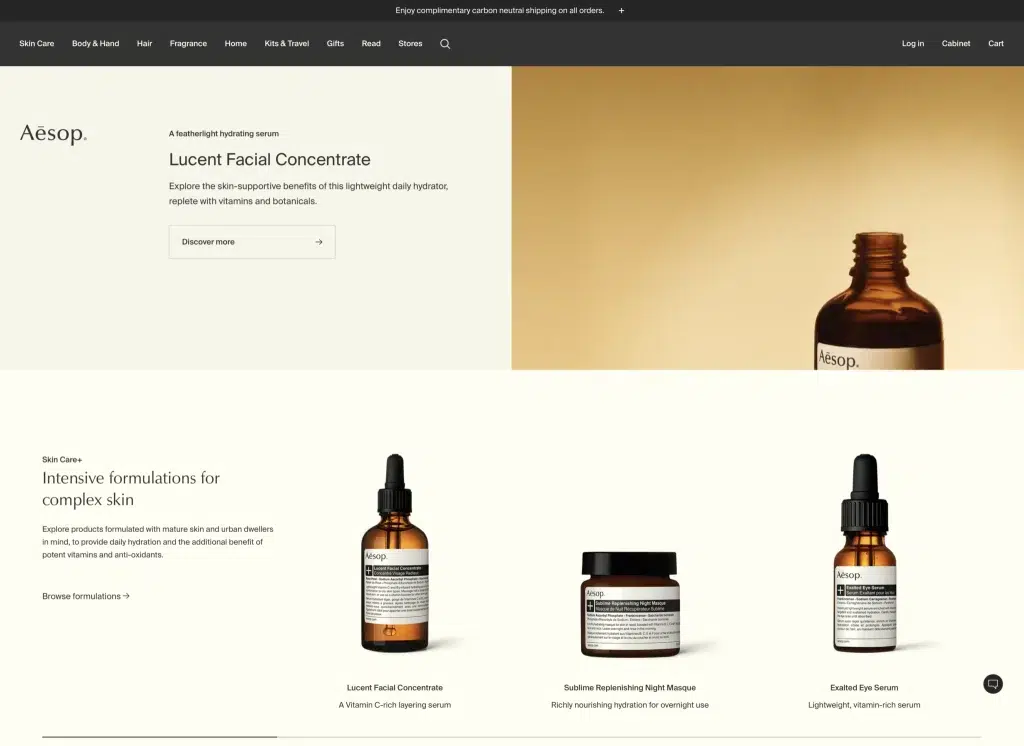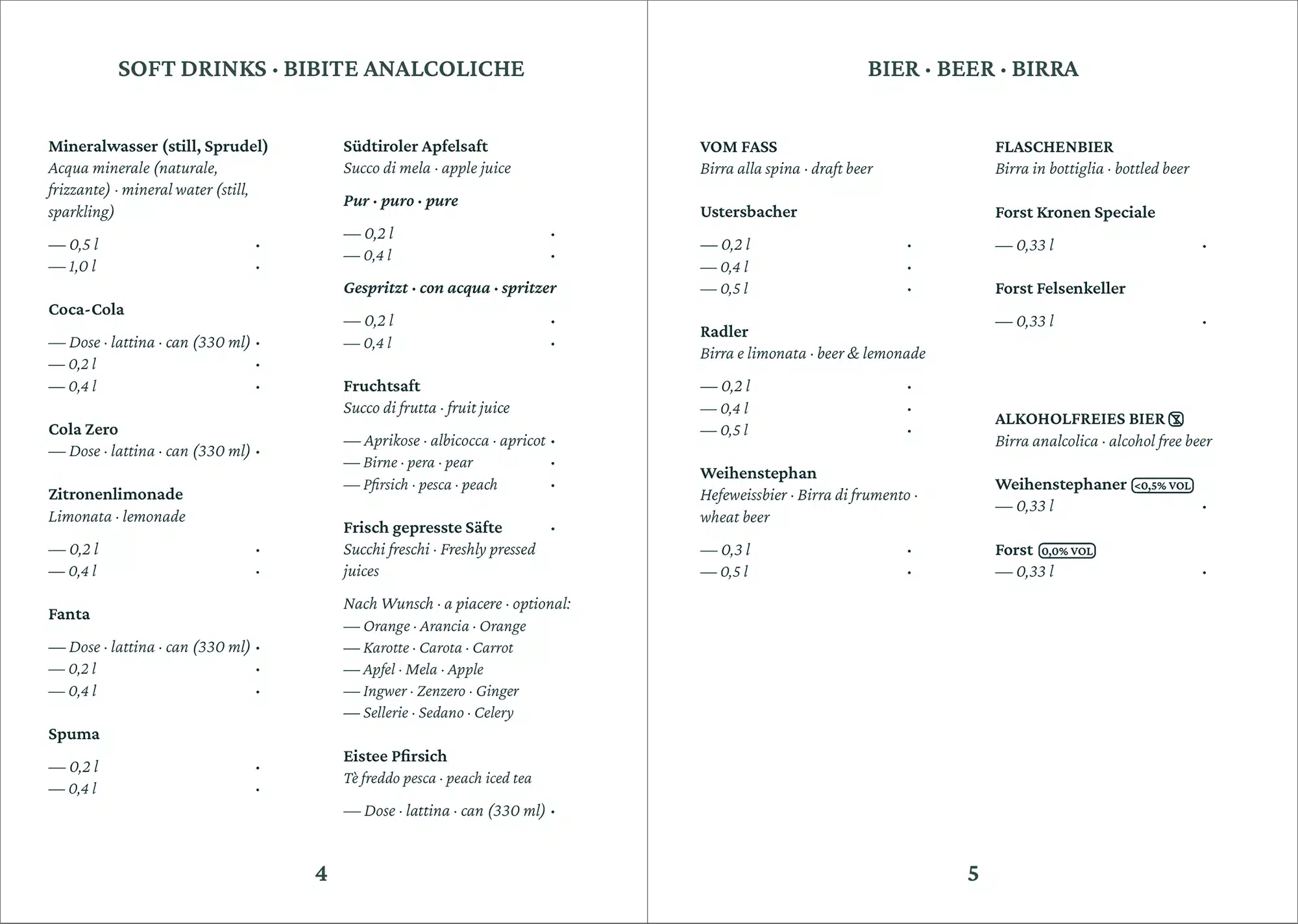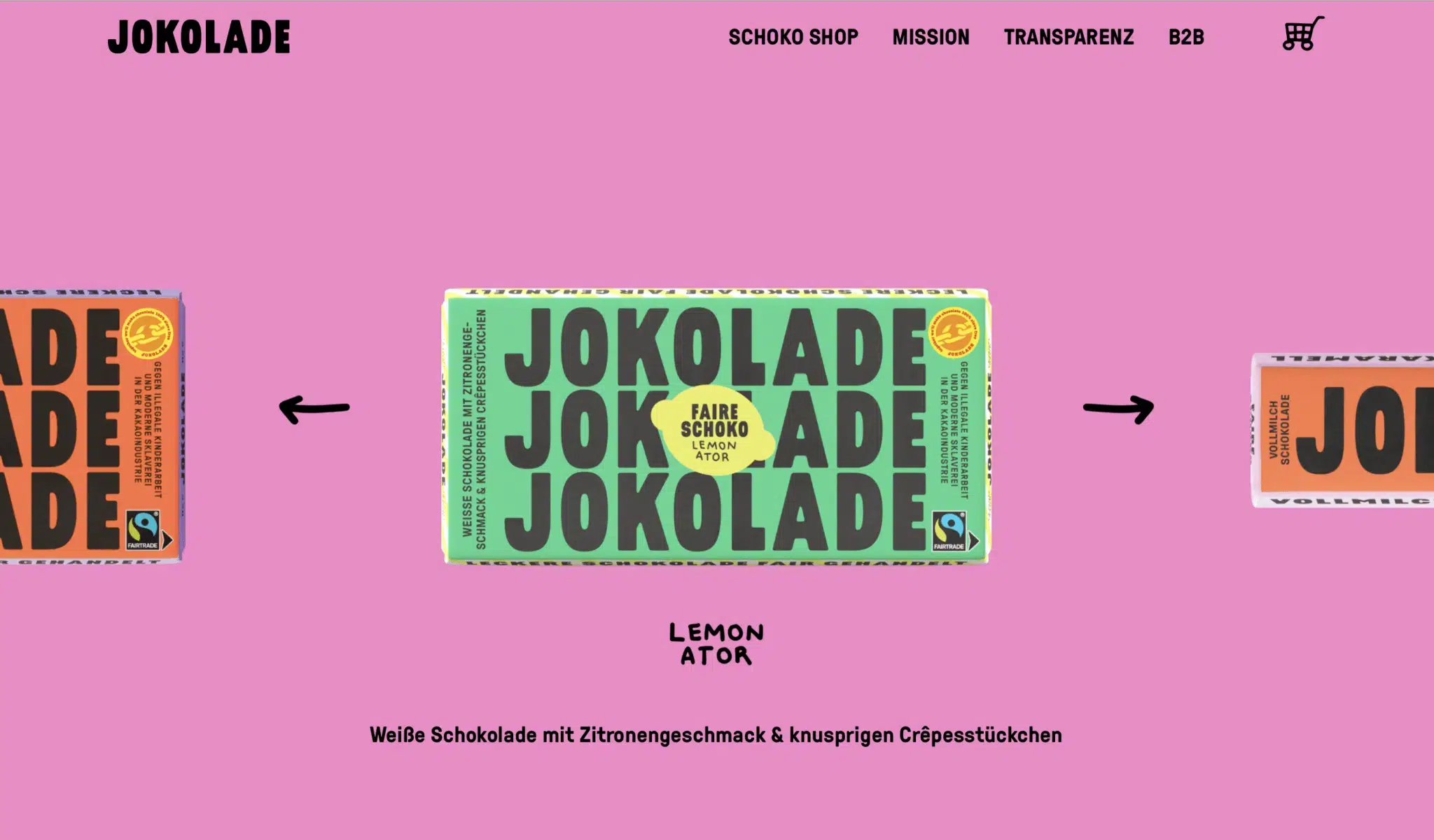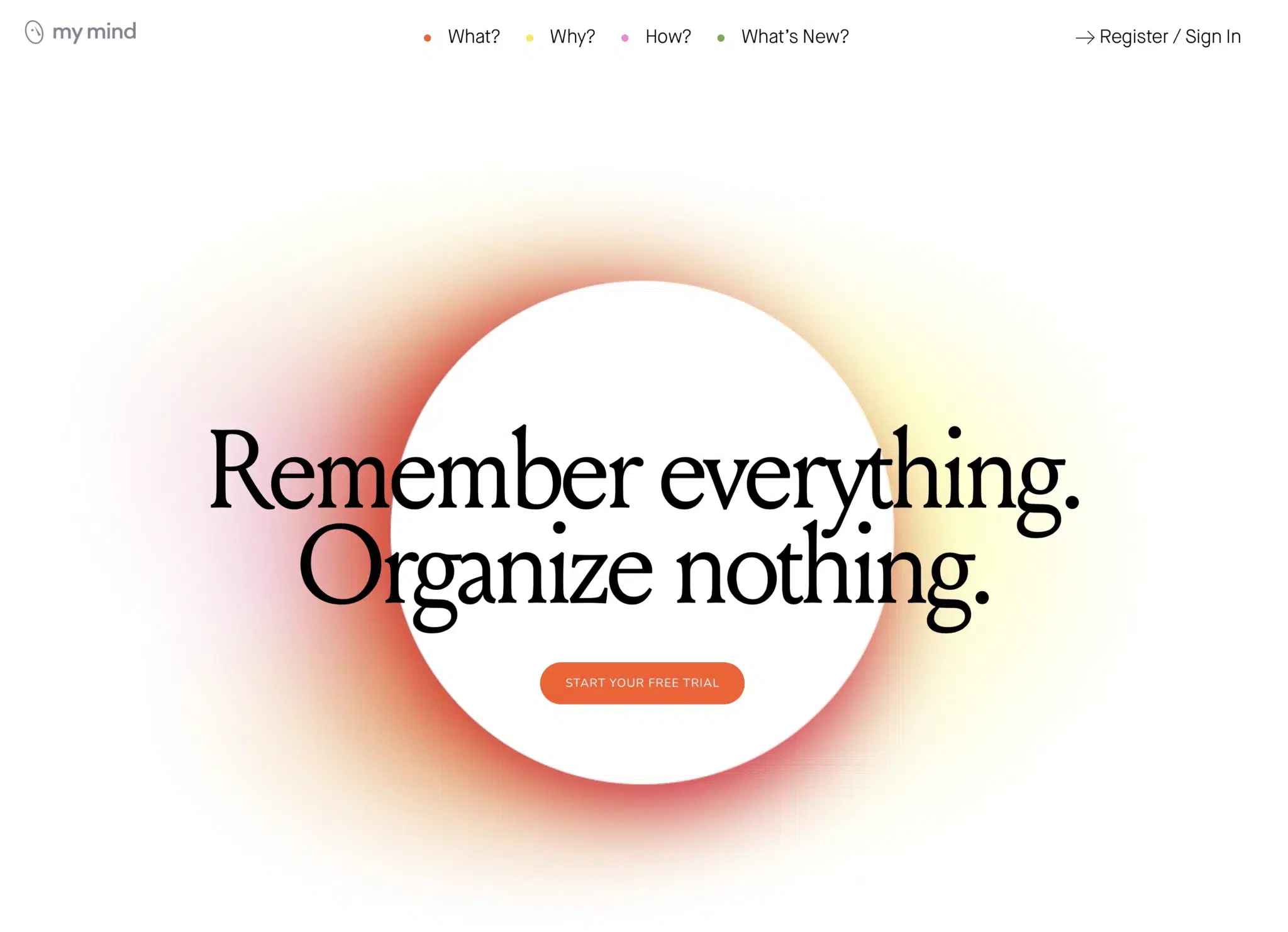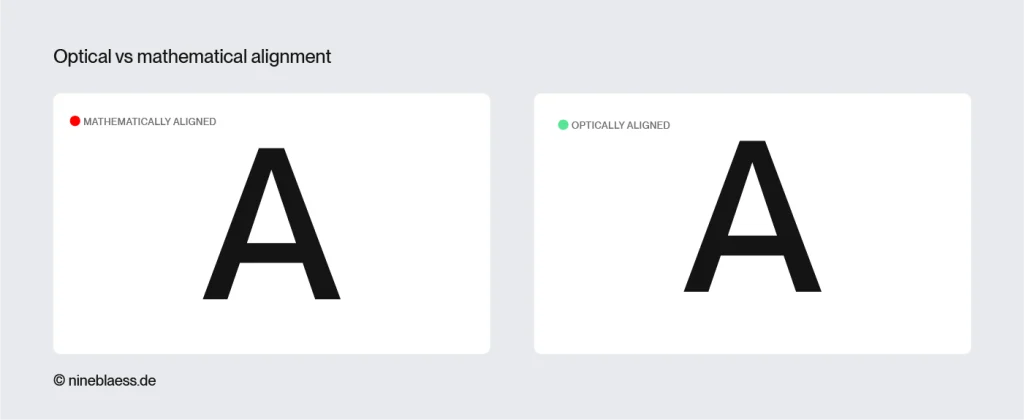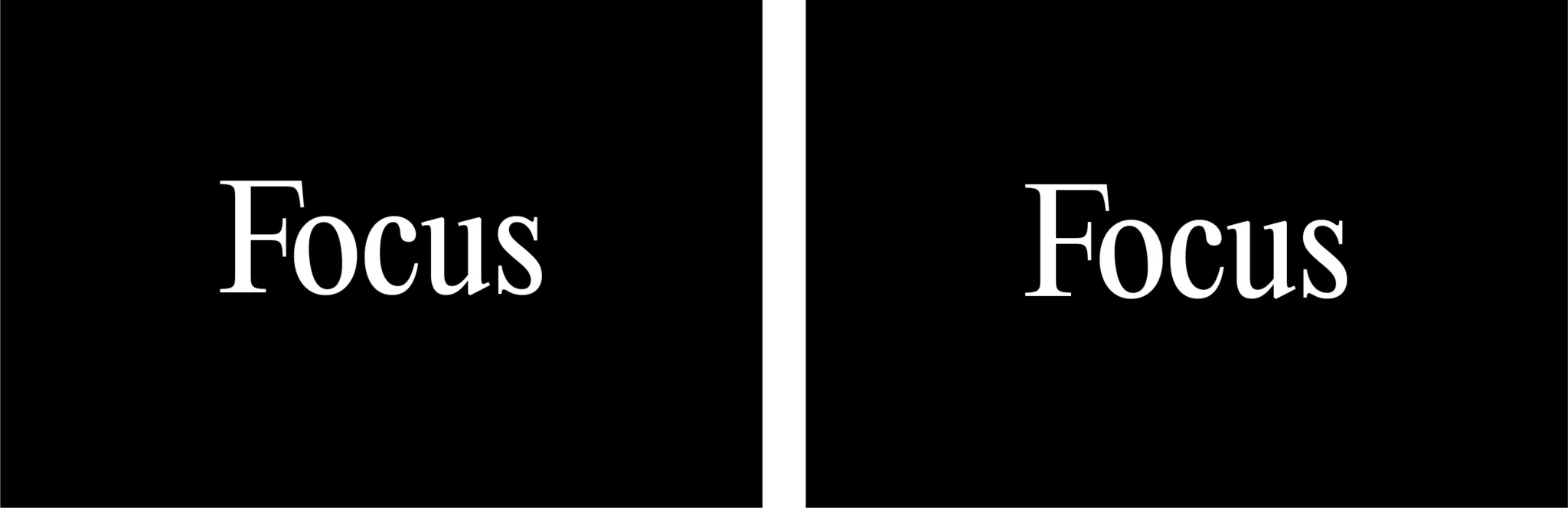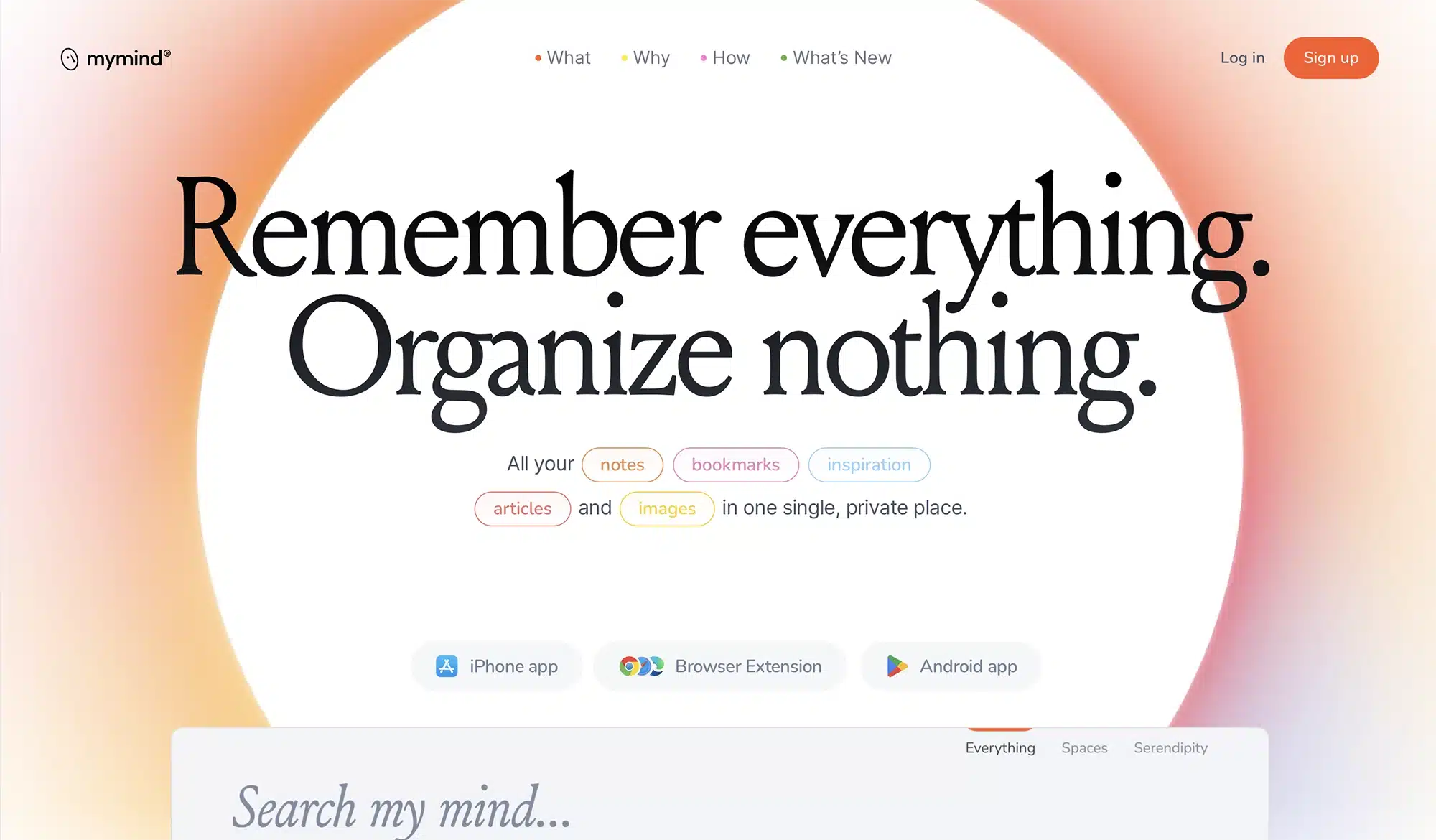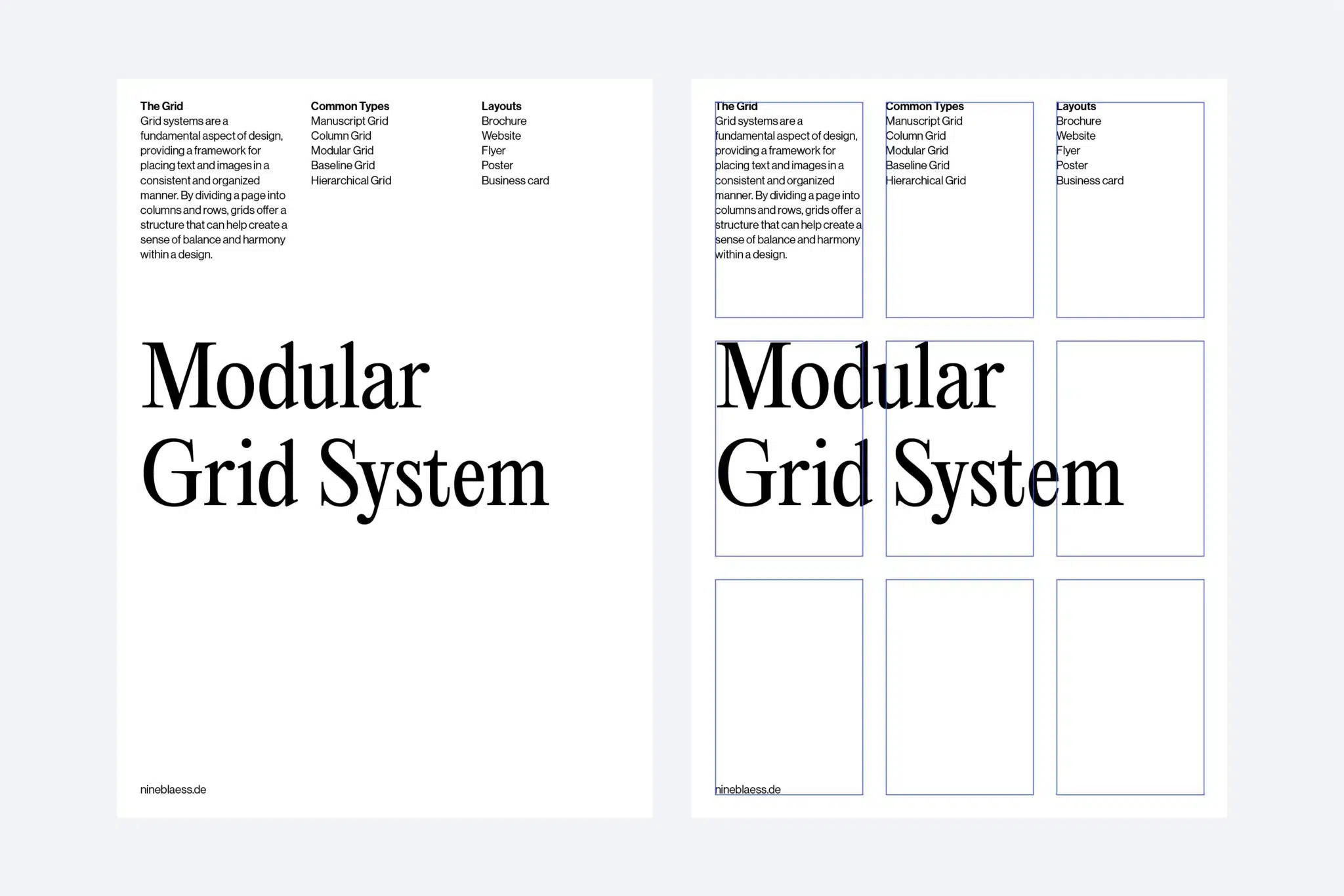
22 Typografie-Tipps für Designer, die besser gestalten wollen als KI
Das Bild zeigt den Schriftzug „Type Tips“ in der Schriftart Editorial New, auf den in Photoshop ein Glas-Filter angewendet wurde. Die Schrift ist zentriert auf einem schlichten schwarzen Hintergrund. Dieses experimentelle Bild dient als Begleitmotiv für einen Blogartikel mit dem Titel „Typografie-Grundlagen: 20 Tipps, um deine Typografie-Skills zu verbessern“.
KI verändert den Designalltag. Viele Aufgaben, die früher von Junior-Designern erledigt wurden, werden heute von Algorithmen übernommen. Das ist keine Katastrophe, aber es bedeutet, dass du als Designer dort punkten musst, wo KI nicht mithalten kann. Ein Bereich, in dem das gelingt, ist die Typografie.
Eine KI kann Pixel perfekt in ein Raster setzen. Sie spürt jedoch nicht, wenn ein Flattersatz nicht optimal gesetzt ist, und sie versteht auch nicht, warum eine Schriftart für eine Zielgruppe funktioniert und für eine andere nicht. Genau das ist dein Vorteil als Designer mit geübtem Auge.
In diesem Artikel findest du 22 Typografie-Tipps, die über die Grundlagen hinausgehen—Details, die eine KI einfach (noch) nicht beherrscht.
Als selbstgelernte Designerin habe ich jahrelang an mir gezweifelt. Doch kaum etwas hat meine Arbeit so stark verbessert wie das Erlernen der Typografie. Hier sind also die Typografie-Tipps, die ich gerne früher gewusst hätte.
1. Berücksichtige die Zielgruppe
Eine Zielgruppenanalyse umfasst mehr als nur demografische Daten wie Alter und Wohnort. Tauche in die Welt der Zielgruppe ein. Was ist ihnen vertraut? Was signalisiert für sie Qualität und was funktioniert bei ihnen gar nicht?
Eine Schrift, die in einem Kopenhagener Designstudio funktioniert, kann für ein Familienunternehmen im ländlichen Neuseeland völlig ungeeignet sein. Eine KI kann zwar Daten analysieren, aber dieses kulturelle Gespür hat sie nicht. Du hingegen schon.
Frag dich also, bevor du startest:
• Für wen mache ich das?
• Was ist diesen Menschen wichtig?
• Wie soll sich das Design für sie anfühlen?
Design-Tipp
Überlege nicht nur, wer deine Zielgruppe ist, sondern auch, wem sie bereits vertraut. Wähle Schriftarten, die eine Verbindung zu dieser Welt herstellen.
2. Nutze professionell designte Schriftarten
Kostenlose Schriftarten können gut funktionieren, werden aber oft zu häufig benutzt. Professionelle Schriftarten bieten mehr Einzigartigkeit, eine größere Auswahl an Schriftschnitten und -stilen sowie vollständige Zeichensätze.
Letzteres ist besonders wichtig, wenn du mit Sprachen wie Deutsch oder Te Reo Māori arbeitest—wie ich, da beide Sonderzeichen wie „ä” oder „ā” benötigen, die viele kostenlose Schriftarten nicht enthalten.
Auch variable Schriftarten sind einen Blick wert. Sie vereinen mehrere Schriftstärken und Stile in einer einzigen Datei und machen Websites schneller. Wenn du aber nur eine oder zwei Schriftstärken brauchst, können einzelne Dateien nach wie vor die bessere Wahl sein.
Design-Tipp
Wenn sich Design abheben soll, investiere in eine hochwertige Schriftart.
3. Nutze eine klare Hierarchie
Jedes Design braucht eine klare Hierarchie, die den Blick lenkt. Die meisten Menschen überfliegen eine Seite, bevor sie sie lesen. Wenn die Informationen nicht klar strukturiert sind, geht deine Botschaft unter. Und wenn Nutzer nicht schnell finden, was sie suchen, verlierst du sie.
Größe, Schriftstärke, Farbe und Schriftstil helfen dabei, den Blick zu lenken.
Die MyMind-Website macht das gut. Das Auge landet zuerst auf der Überschrift, dann auf dem Button und schließlich auf der Navigation. Sogar die Kreisform leitet den Blick natürlich zur zentrierten Überschrift.
Screenshot der Startseite von MyMind. Die typografische Hierarchie ist hier ganz klar: Eine große Serifenschrift dominiert als Überschrift, gefolgt von einer Unterüberschrift und den Navigationselementen.
Design-Tipp
Lege vor dem Designen fest, was als Erstes, Zweites und Drittes wahrgenommen werden soll und baue dein Layout dementsprechend auf. Es ist einer dieser einfachen Typografie-Tipps, die einen großen Unterschied beim fertigen Design ausmachen.
4. Verwende Rastersysteme
Raster sorgen für Struktur. Sie ordnen Inhalte in Spalten und Zeilen an und sorgen dafür, dass nichts fehl am Platz wirkt.
Es gibt verschiedene Arten von Rastern—hier sind die wichtigsten:
• Manuskriptraster haben eine Haupttextspalte. Sie sind ideal für Bücher und längere Texte.